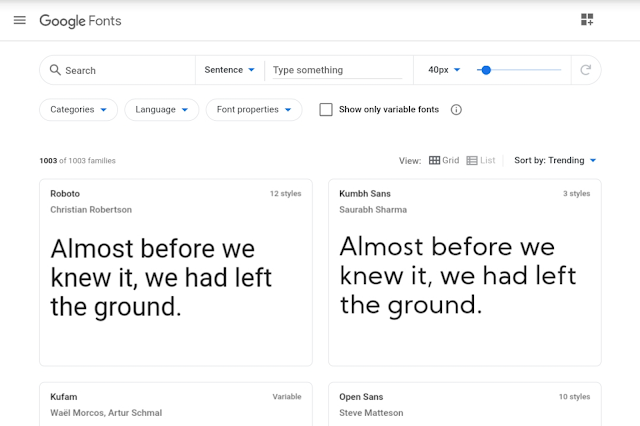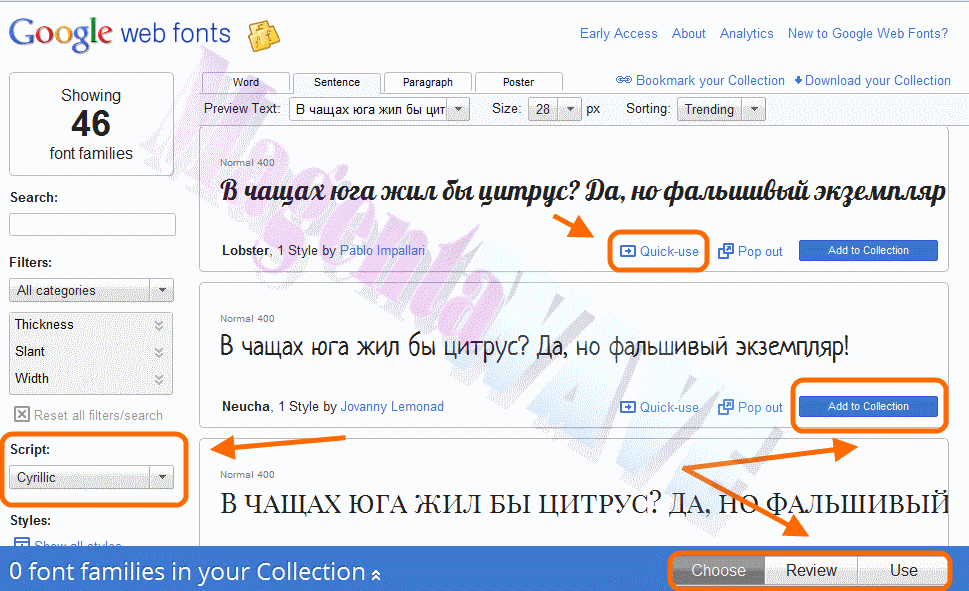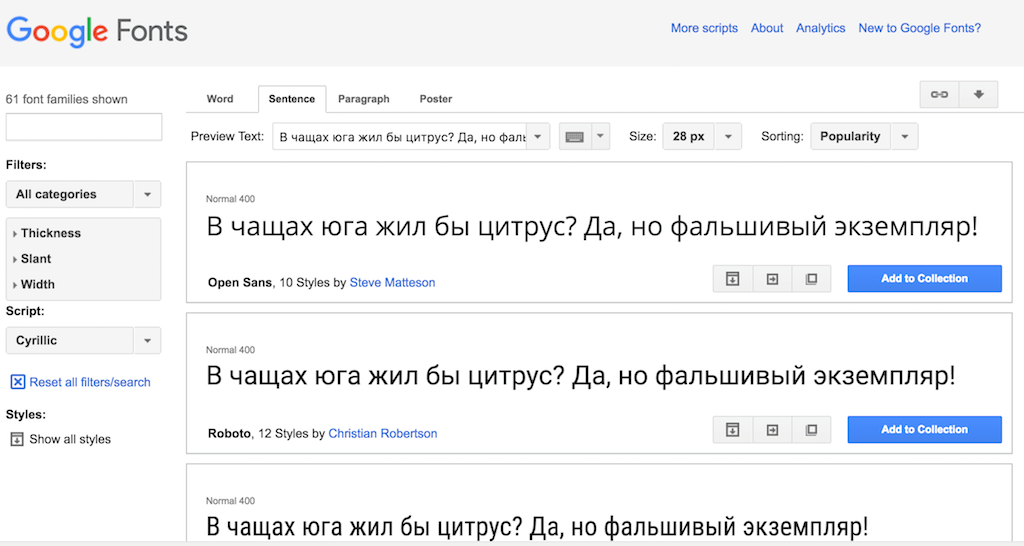
Шрифты google: Google Fonts / Настройка шрифтов для проекта
5 лучших бесплатных шрифтов с Google Fonts для сайта — Гаяне Гаспарян на vc.ru
Шрифт — это буквально почерк вашего бизнеса, важный визуальный элемент для создания правильного восприятия вашего бренда. Текст зачастую выступает главным способом коммуникации компании с клиентом. Использование гармоничных сочетаний шрифтов на сайте, в рекламных материалах и других составляющих айдентики помогает сформировать образ компании, отражающий ее позиционирование. То, какой шрифт используется в веб-дизайне, косвенным образом влияет и на конверсию: посетители интернет-портала более лояльны к контенту, представленному читабельными — чёткими и различимыми шрифтами, в этом случае они с большей вероятностью станут постоянными клиентами.
В подборке Google Fonts более 1000 бесплатных шрифтов, которые подходят для коммерческого использования, вот 5 лучших:
Montserrat – лучший шрифт без засечек. Шрифт очень удобный, подходит не только для заголовков, но и для текстов, так что необязательно даже подбирать ему шрифтовую пару. У этого шрифта примерно одинаковое соотношение ширины и высоты, поэтому он удобен практически для всех типов проектов. Поддерживает кириллицу и латиницу и имеет больше 10 начертаний.
Raleway — это элегантный шрифт без засечек, предназначенный для заголовков и других текстов с большим кеглем.
Первоначально его разработал Мэтт Макинерни только в тонком весе, а в 2012 году Пабло Импаллари и Родриго Фуэнзалида расширили его в семейство из девяти начертаний.Стиль этого шрифта добавляет свежести любому проекту, несмотря на строгость форм. Raleway подходит именитым брендам, которые хотят идти в ногу со временем. Стоит обратить на него внимание, если вы хотите подчеркнуть элегантность или минималистичность проекта.
Open Sans — семейство свободных шрифтов, разработанных Стивом Мэттисоном по заказу Google. По данным Google, он был спроектирован с «прямым штрихом, открытыми формами и нейтральной, но дружественной внешностью» и «оптимизирован для удобочитаемости при печати, в веб- и мобильных интерфейсах».
Rubik — шрифт без засечек со слегка закруглёнными углами. Лёгкий, мягкий шрифт будет хорошо смотреться в тексте для чтения и подойдёт проекту практически любой тематики. Он — наша любимая альтернатива платного Daxline.
Merriweather – изящный шрифт с засечками, который разработали специально для комфортного чтения на электронных устройствах. У шрифта мягкие засечки и открытые формы, поэтому он практически универсален. Его рекомендуют использовать в паре с самим собой либо с рублеными шрифтами для наборного текста. Например, с Open Sans или Roboto.
Не забывайте проверять, все ли необходимые вам знаки есть у выбранного шрифта. Иначе может получиться неловкая ситуация, когда в понравившейся гарнитуре не будет знака рубля или буквы «ё».
10 лучших бесплатных кириллических шрифтов с Google Fonts | GeekBrains
Подборка актуальных и красивых шрифтов, которые вы можете использовать для коммерческих и персональных проектов бесплатно
Разработка дизайна для сайта или проекта — трудоёмкий процесс, в начале которого важно принять правильные стилистические решения. Дизайнерам есть над чем подумать: от цветовой схемы и логотипа до навигации и вёрстки контента. Но самое сложное всё-таки в том, чтобы объединить все эти составляющие стиля сайта в одну сбалансированную и цельную концепцию.
Типографика — важная часть этого единства. Мы уже рассматривали основы работы с текстом, а теперь разберёмся со шрифтами. Как только пользователи получают первые впечатления от сайта с помощью цвета, они начинают воспринимать информацию непосредственно через текст. Хорошо читаемый, красивый и органичный шрифт может повлиять на их решение о том, остаться ли на сайте.
Выбор шрифтов слишком велик, поэтому возникает много вопросов. С чего начать? Что с лицензией? Гротеск или антиква? Как понять, что шрифт удобочитаемый? А что он не устарел? Какие шрифты отлично работают в заголовках, а какие в наборном тексте? Ох, это слишком сложно, особенно на начальном этапе.